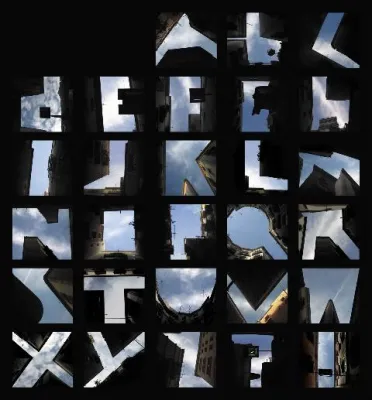
Die Leipziger Typotage 2011: „Schrift und Typografie in der zeitgenössischen Kunst“
(openPR) Schrift ist immer noch der Träger von Informationen. Im täglichen Leben der Menschen ist sie allgegenwärtig. Ihre Gestaltung – groß/klein, fett/dünn, schlicht oder grell – beeinflusst die Wahrnehmung. Doch Schrift offenbart sich auch jenseits gewohnter Sehweisen. Wenn sie beispielsweise zum Mittel künstlerischen Ausdrucks wird, entstehen neue und überraschende Erscheinungsformen. Einen Blick auf diese Funktion von Schrift werfen die Referenten und Gäste der Leipziger Typotage am 28. Mai 2011 unter dem Thema „Die geheime Macht der Buchstaben. Schrift und Typografie in der zeitgenössischen Kunst“.
Die neun Referenten der 17. Leipziger Typotage beleuchten in Vorträgen die Funktion und Wirkung von Schrift im westlichen Sprachraum und geben Einblick in die unterschiedlichen Erscheinungsformen, in denen sich Schrift und Typografie wiederfinden können. Gemeinsam mit einem Fachpublikum diskutieren sie das Thema aus dem Blickwinkel der Kunst, des Grafik-Designs, der Typografie und der Psychologie.
Referenten und Vorträge:
Alexander Branczyk, Der geschriebene Garten
Barbara Dechant & Anja Schulze, Wer A sagt, muss auch B sagen: Das Buchstabenmuseum Berlin
Dr. Christian Gutschi, Emotionale Wirkung von Druckschriften
Lars Harmsen & Julia Kahl, SHORTCUT BABYLON: Slanted Blog & Magazine
Will Hill, Painted Words: language and letterform in 20th century visual practice
Sascha Kittel, Das urbane Zeichensystem der Leipziger Kryptogesellschaft
Pantea Lachin, Kinetische Typografie
Prof. Andrea Tinnes & Jenny Baese, Die große Kunst des kleinen ABC
Prof. Sabine Golde & Dr. Reinhard Schubert, Moderation
Leipziger Typotage 2011
Thema: Die geheime Macht der Buchstaben. Schrift und Typografie in der zeitgenössischen Kunst